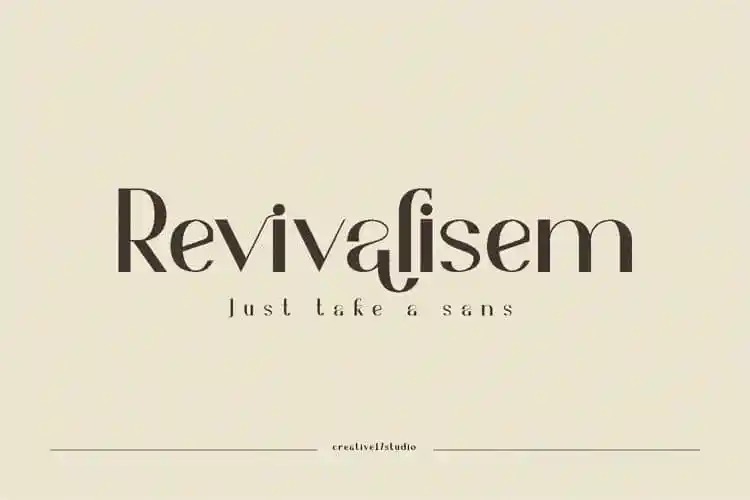
Revivalisem Sans Serif Font – Download Grátis
Revivalisem Sans Serif é uma elegante tipografia sans-serif desenvolvida por Irfan Hidayat. Este tipo de letra oferece várias ligaturas para aumentar a sensação de prestígio em seu projeto. Revivalisem vem com letras maiúsculas e minúsculas completas, números, marcadores de pontuação e ligações, além de letras alternativas e suporta múltiplas línguas, tornando-a facilmente adequada para uma variedade de projetos de design. Seus usos incluem o branding da moda e a editoração, mas sua versatilidade faz dele um escolha perfeita para projetos que exigem simetria e sofisticação.